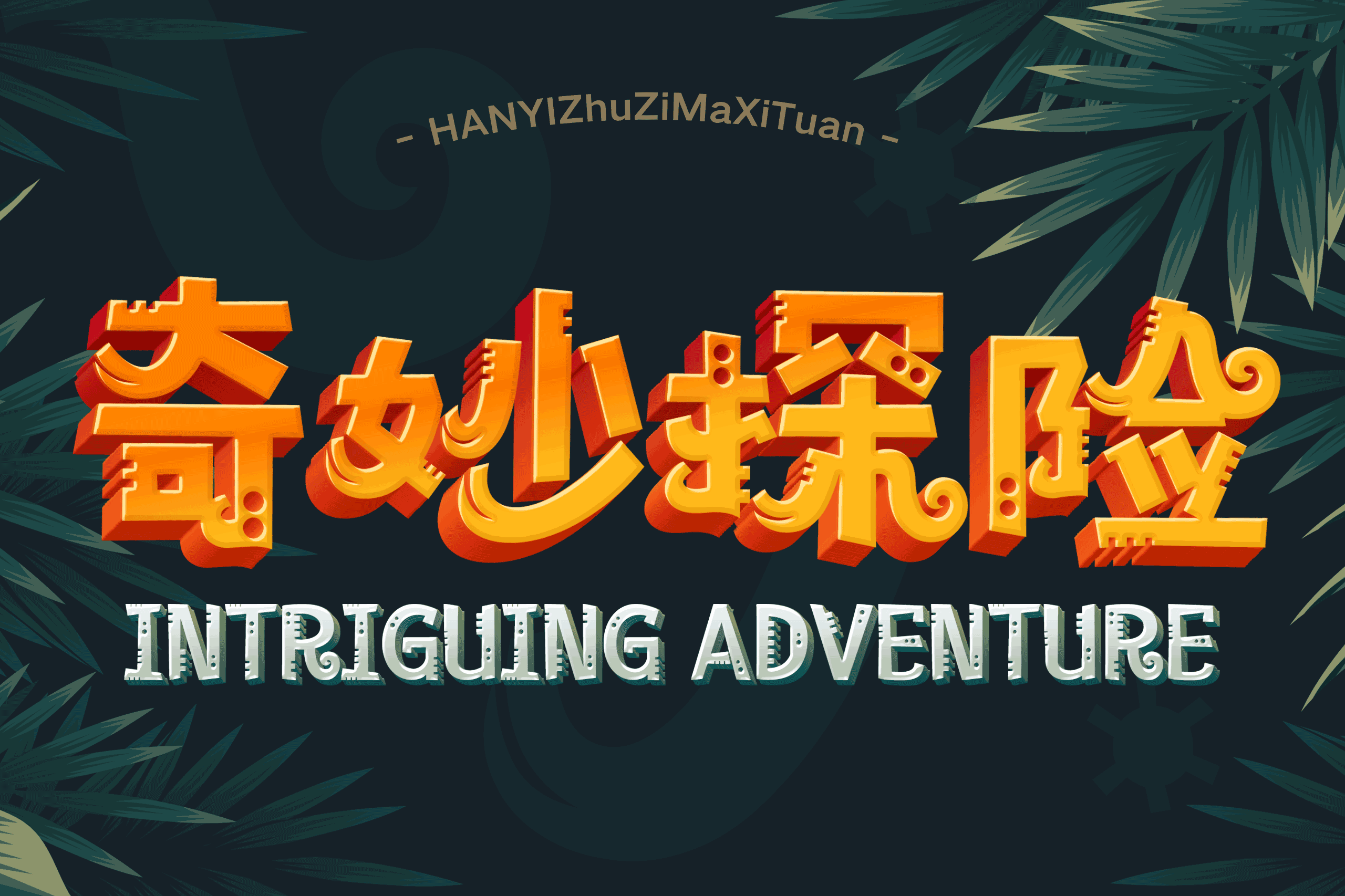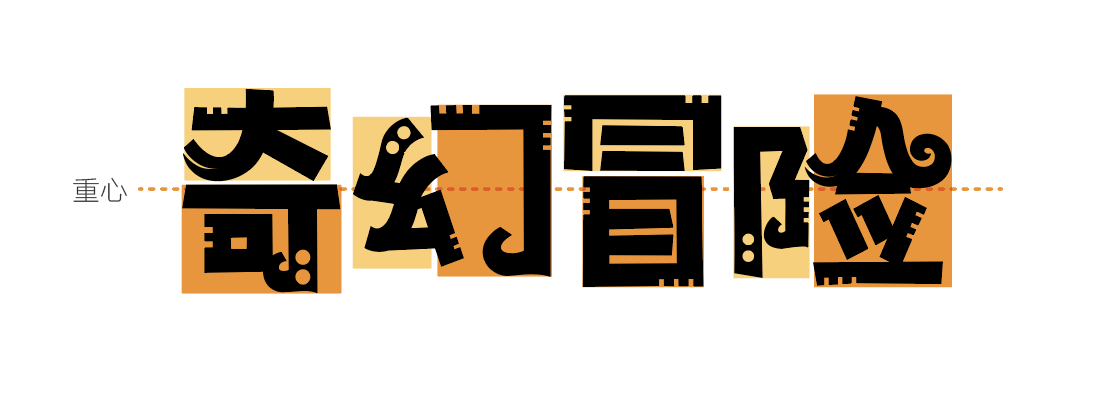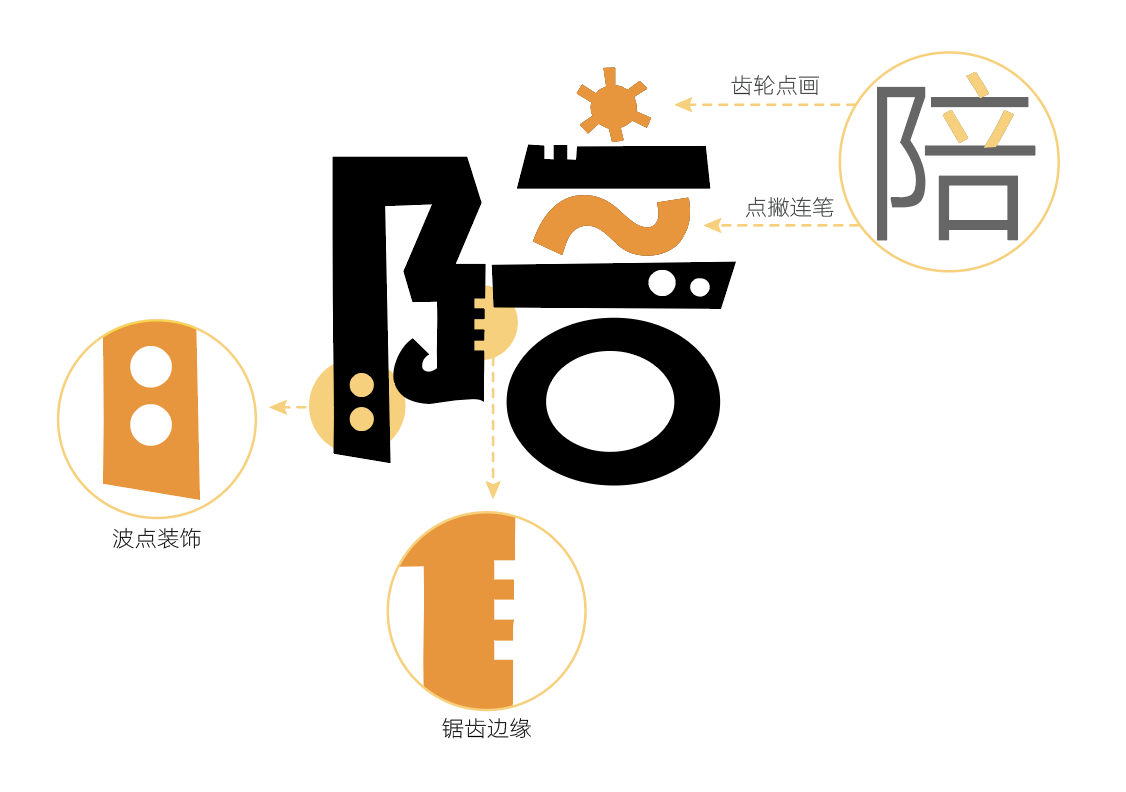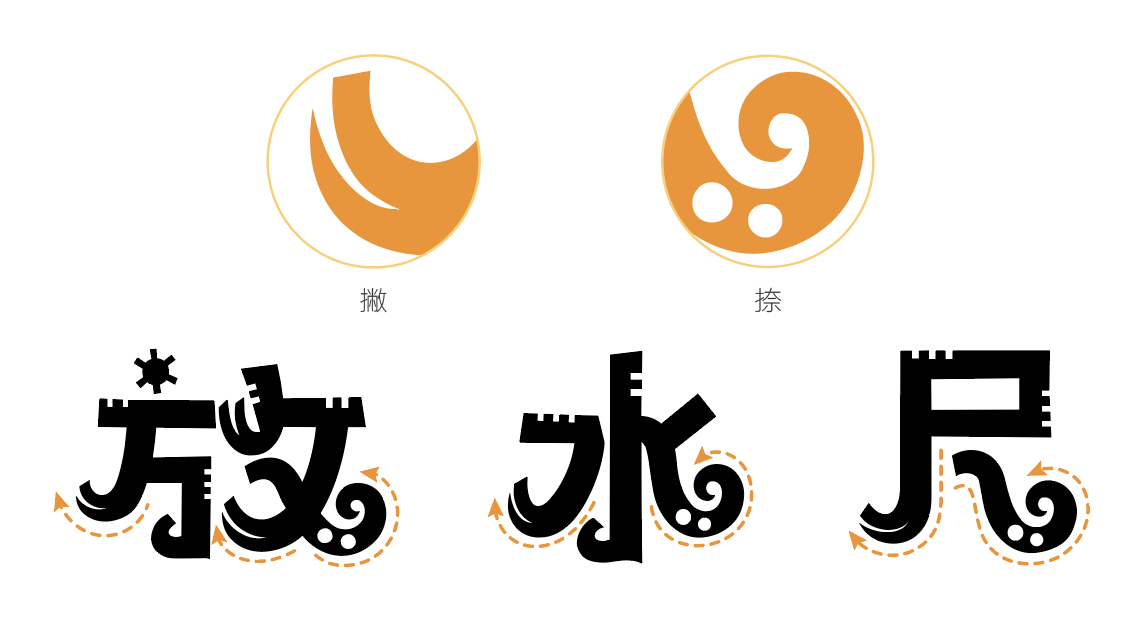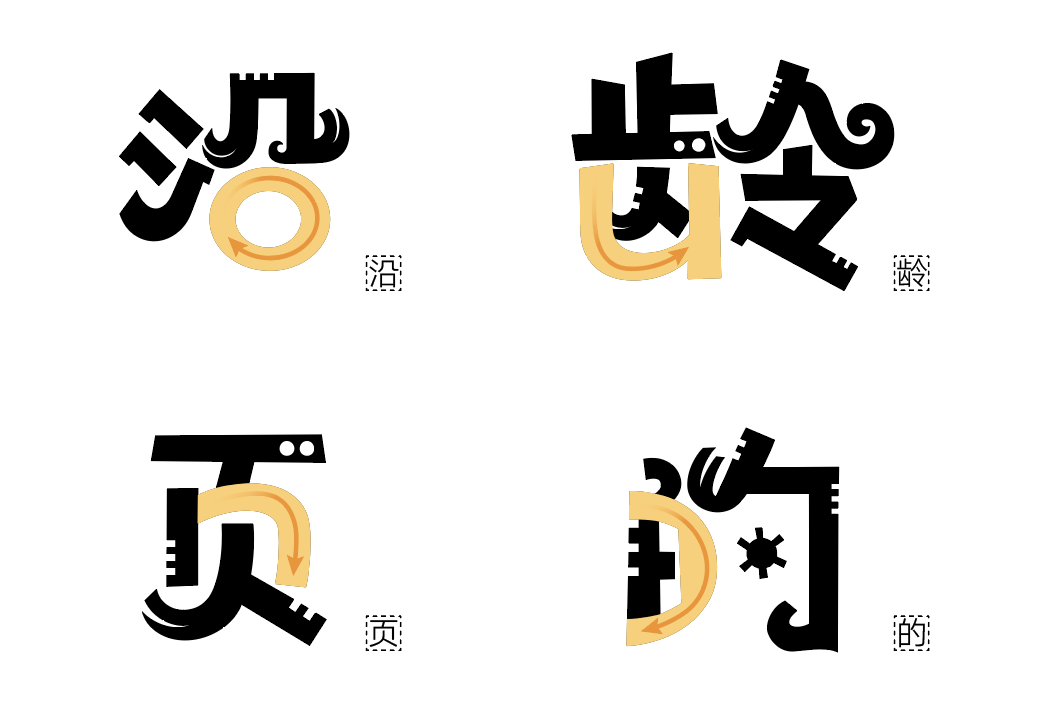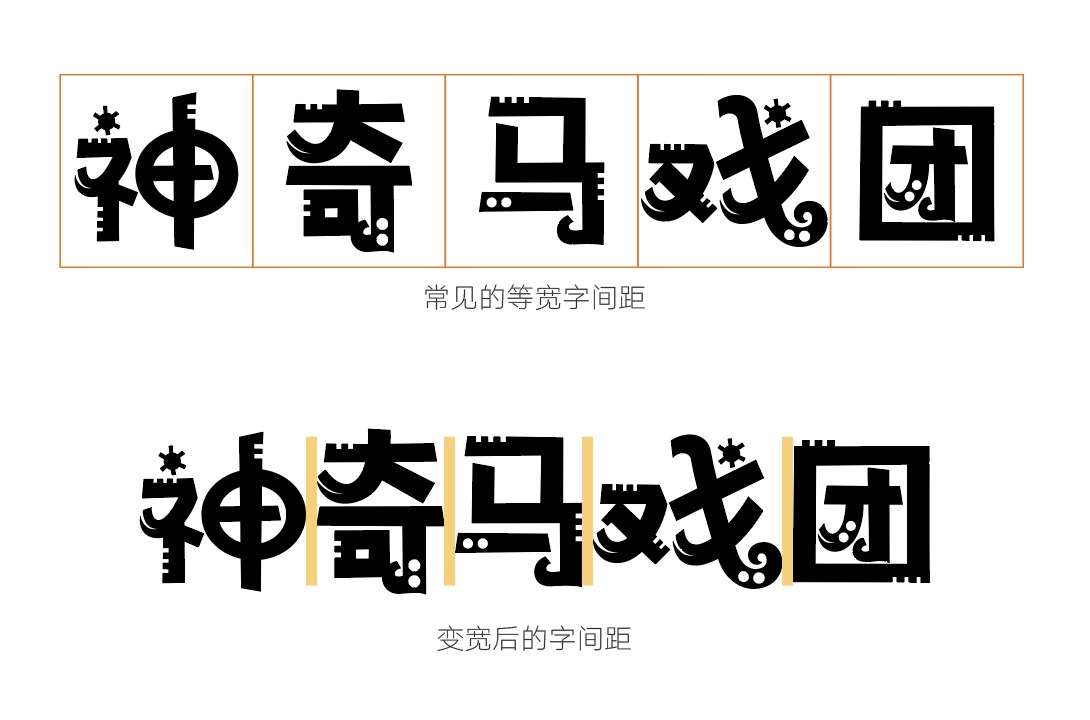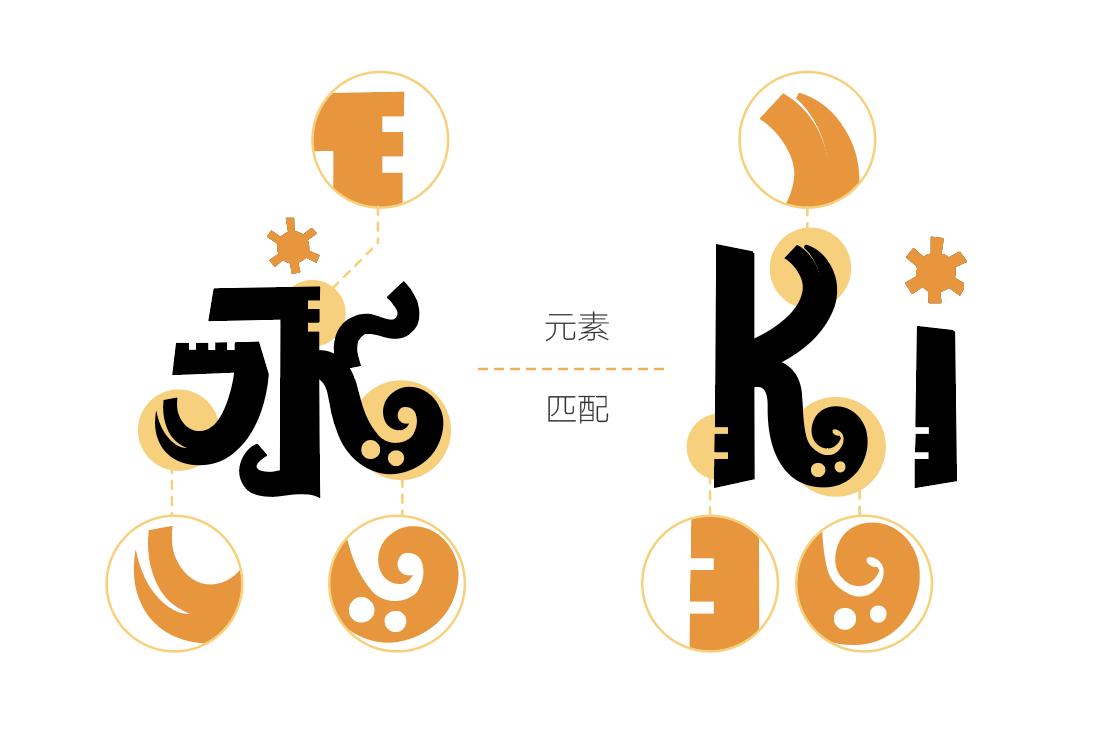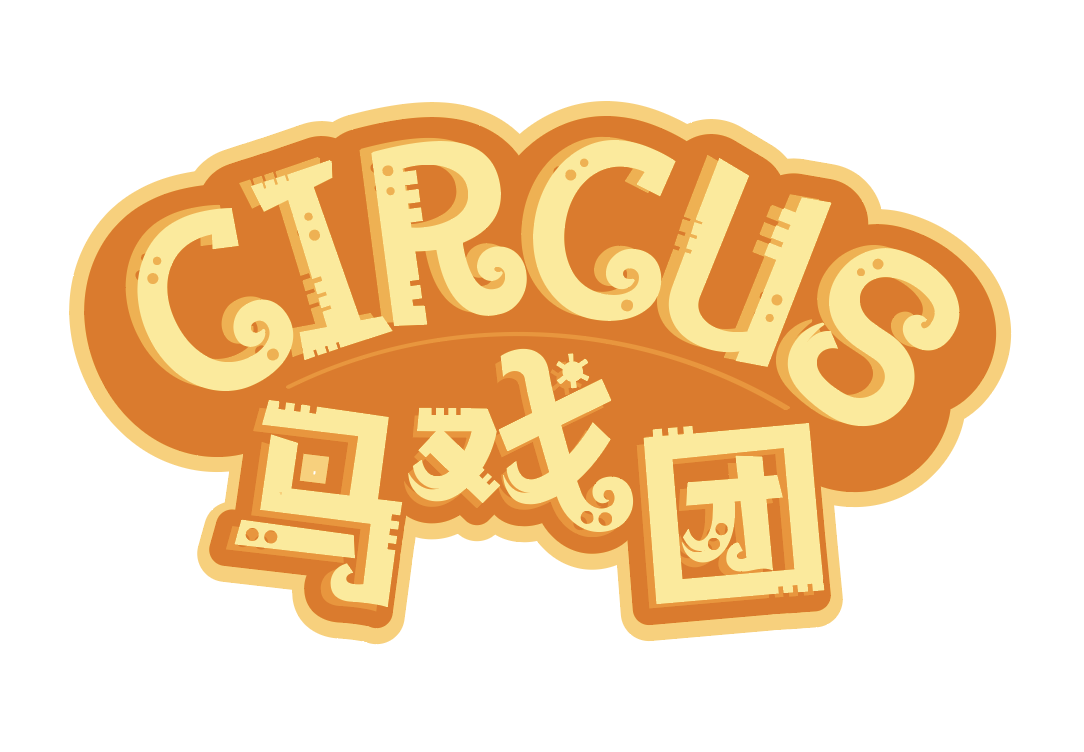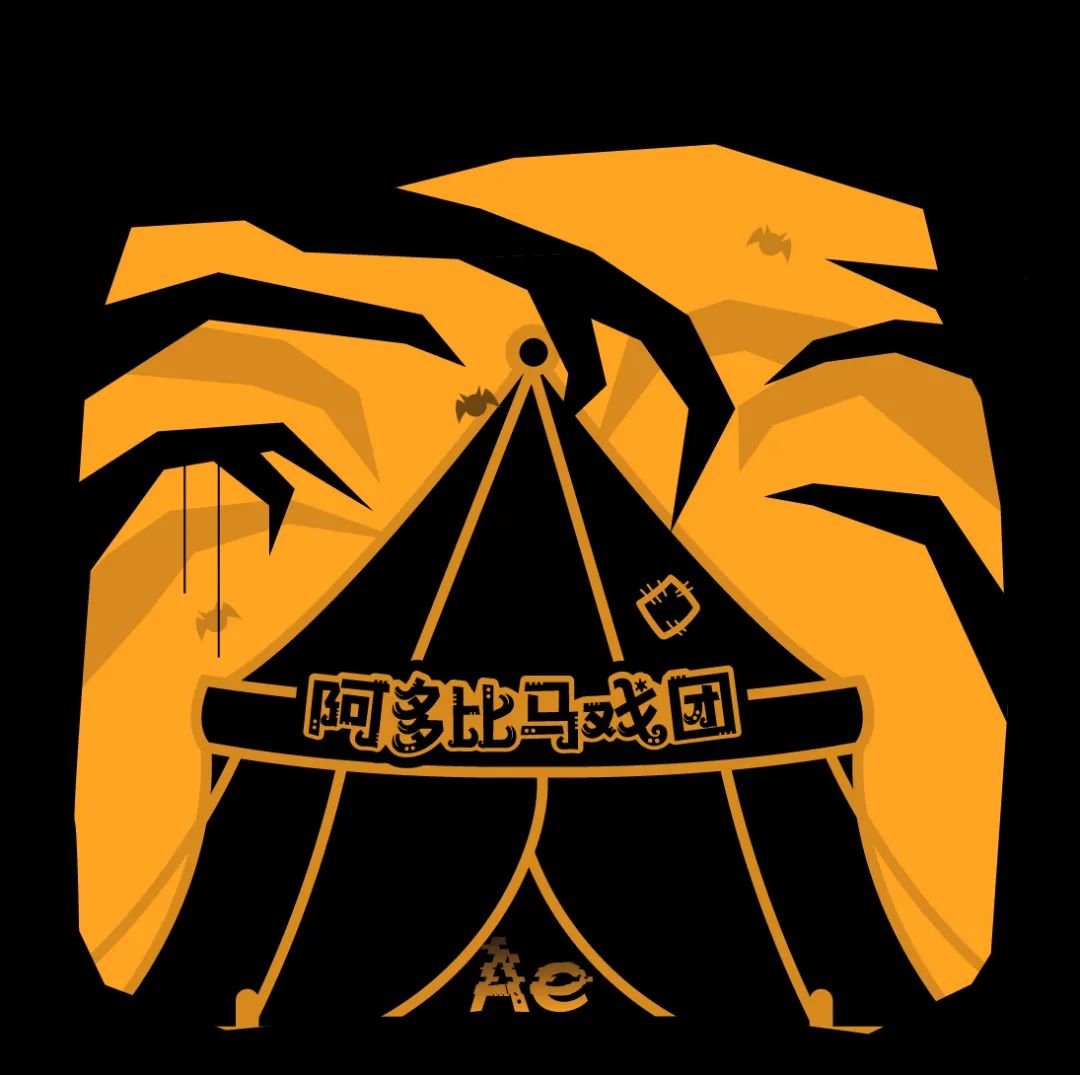
汉仪铸字马戏团字体介绍,汉仪铸字马戏团设计灵感
汉仪铸字马戏团 | 整体特点
汉仪铸字马戏团是一款集趣味性和装饰性于一体的创意字体,无论是字体的笔画还是装饰元素,都有强烈的卡通意味,就像会变魔术玩杂耍的马戏团一样,带给你新奇的体验。
汉仪铸字马戏团 | 字面大小不一
“汉仪铸字马戏团”在保持重心一致的前提下,依据字体结构而呈现出大小不一的节奏变化,非常灵动可爱。
汉仪铸字马戏团 | 笔画形态多变
在不影响整体识别度的前提下,“汉仪铸字马戏团”的“点撇”运用连笔的特点,增强了书写感和流畅度。还有齿轮形状的点画和带有波点、锯齿边缘装饰的笔画,给人一种惊奇怪诞的感觉。
“撇”的末尾加入“拖笔”的特点,有一种用毛刷书写的感觉;“捺”的末尾则是像“章鱼腿”一样,向上弯曲成卷。
“汉仪铸字马戏团” 在部分“口”字结构和折角处融入了柔和流畅的曲线,使字体更加生动新颖。
汉仪铸字马戏团 | 技术特点
由于“汉仪铸字马戏团”不同文字的字面差异较大,考虑到排版使用上的体验感,我们在技术上采用了字间距变宽的处理方式,使字体的排版效果更加舒适自然。
汉仪铸字马戏团 | 中西文匹配
“汉仪铸字马戏团”的西文字母有着和中文一样奇幻可爱的装饰元素,中西文搭配使用十分和谐。
汉仪铸字马戏团 | 案例展示